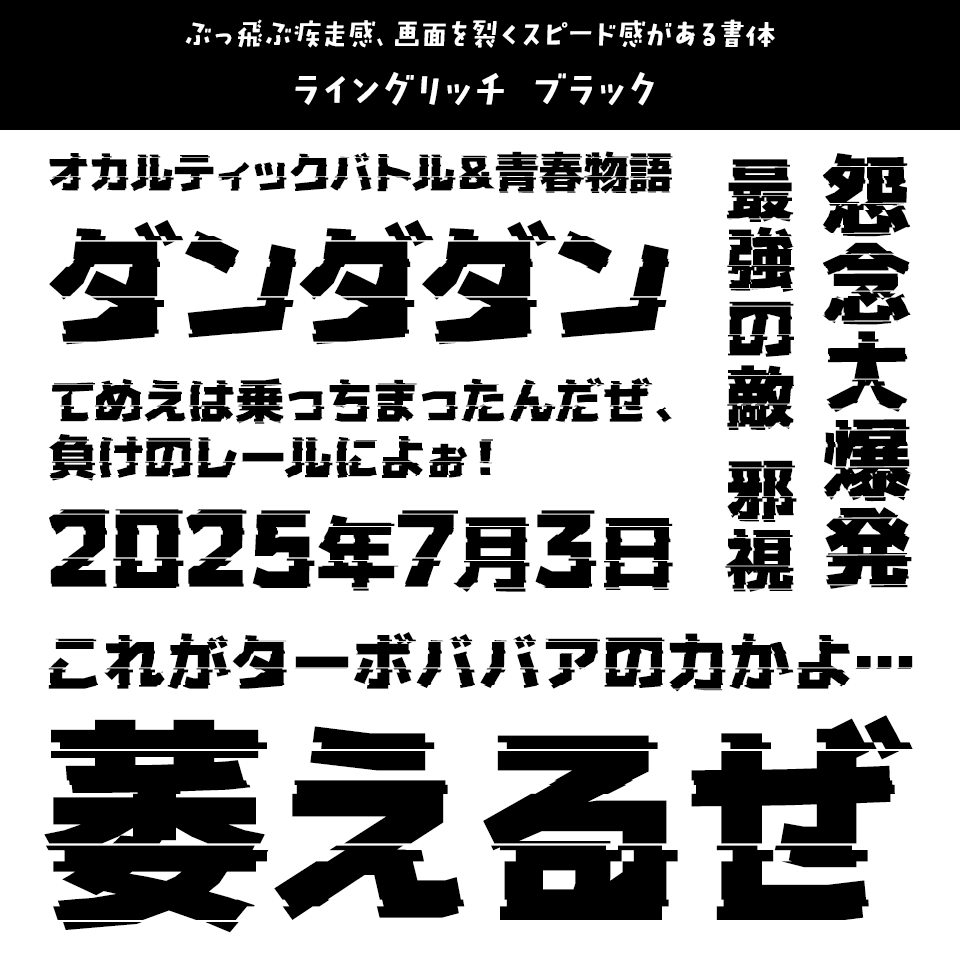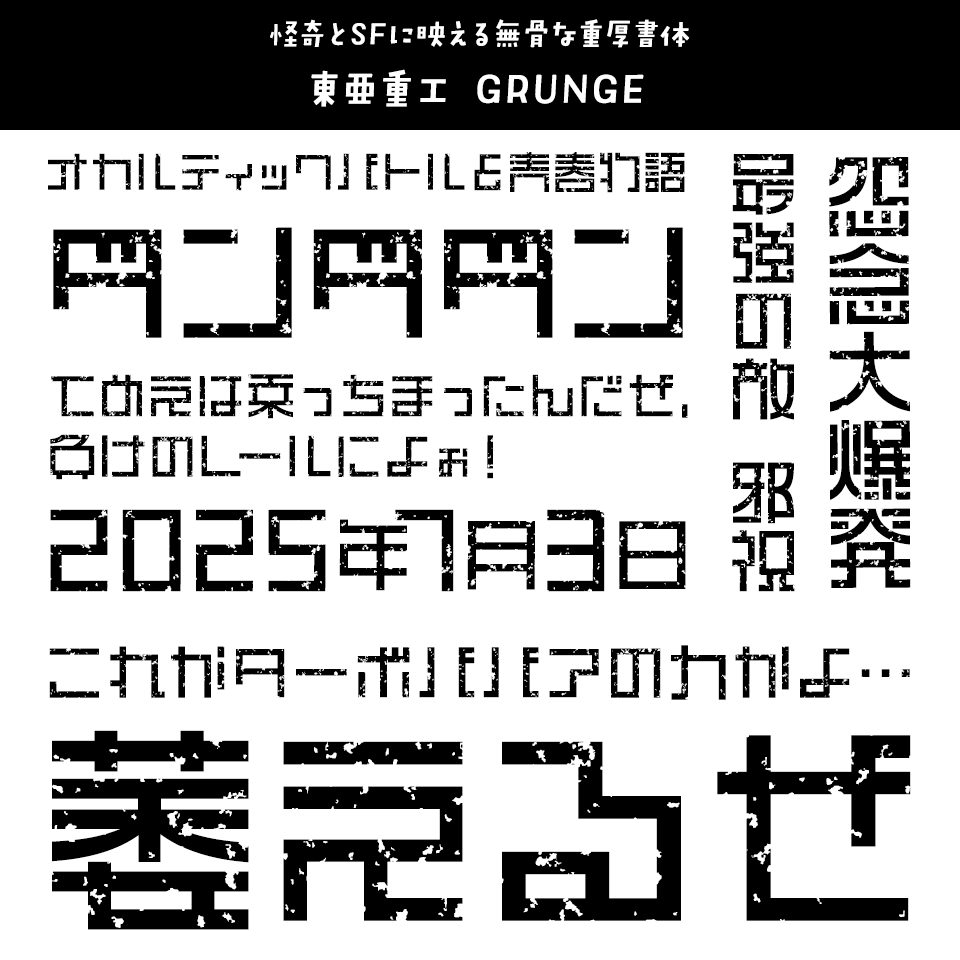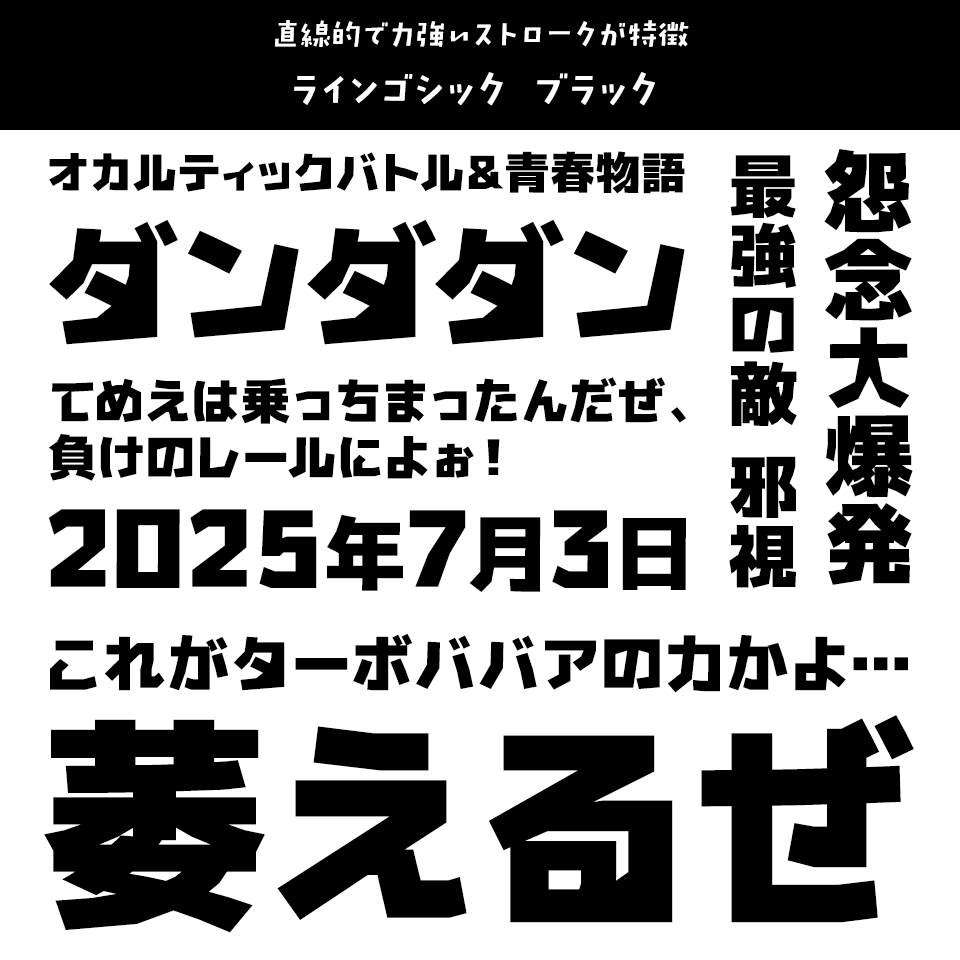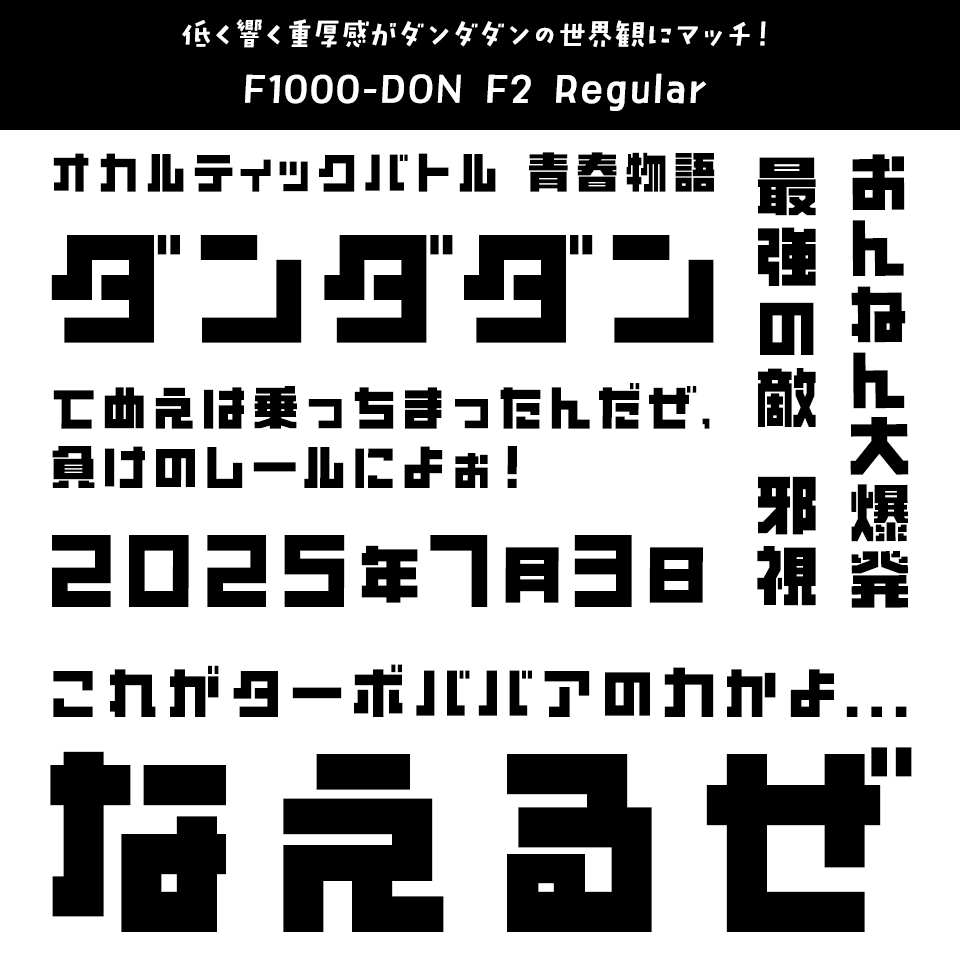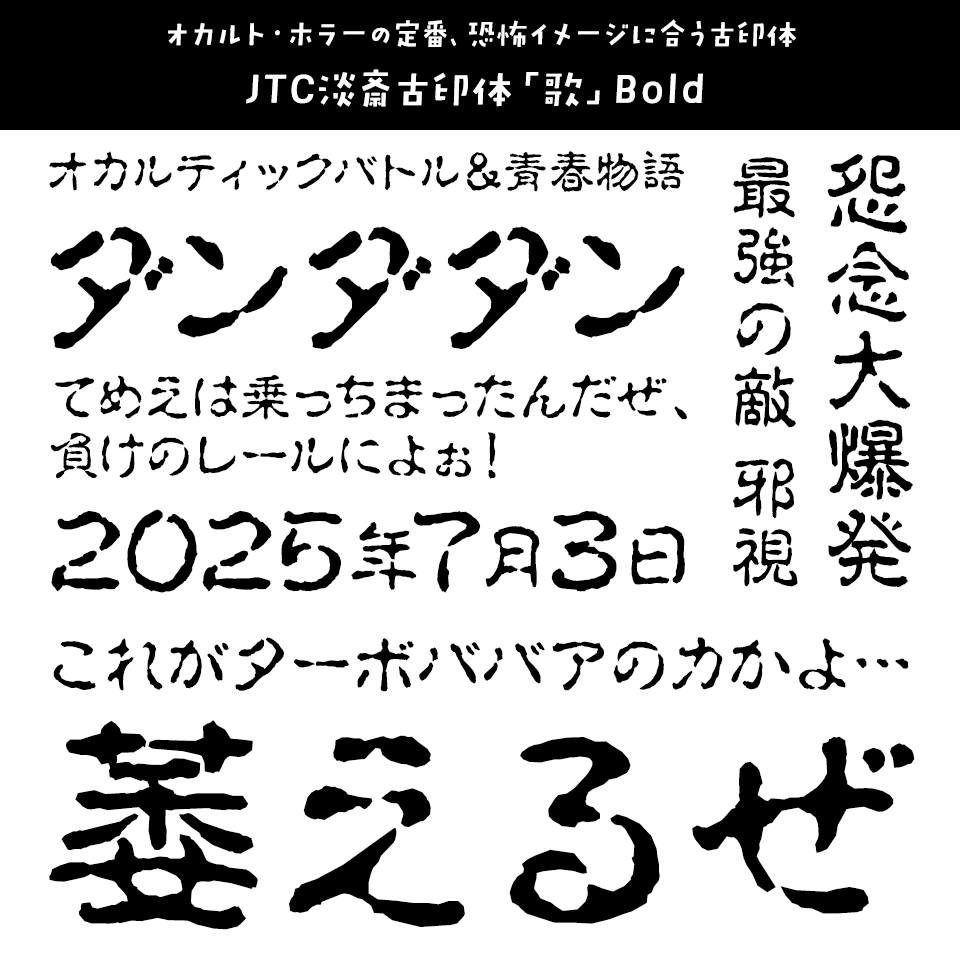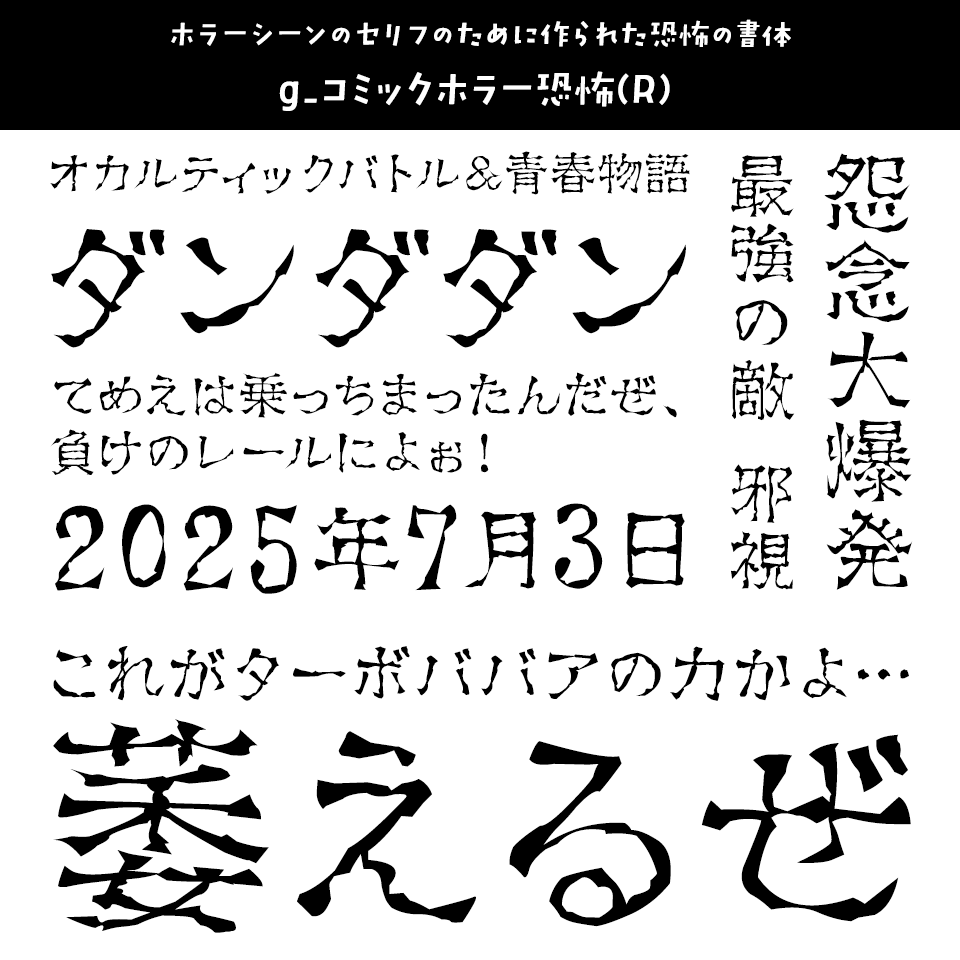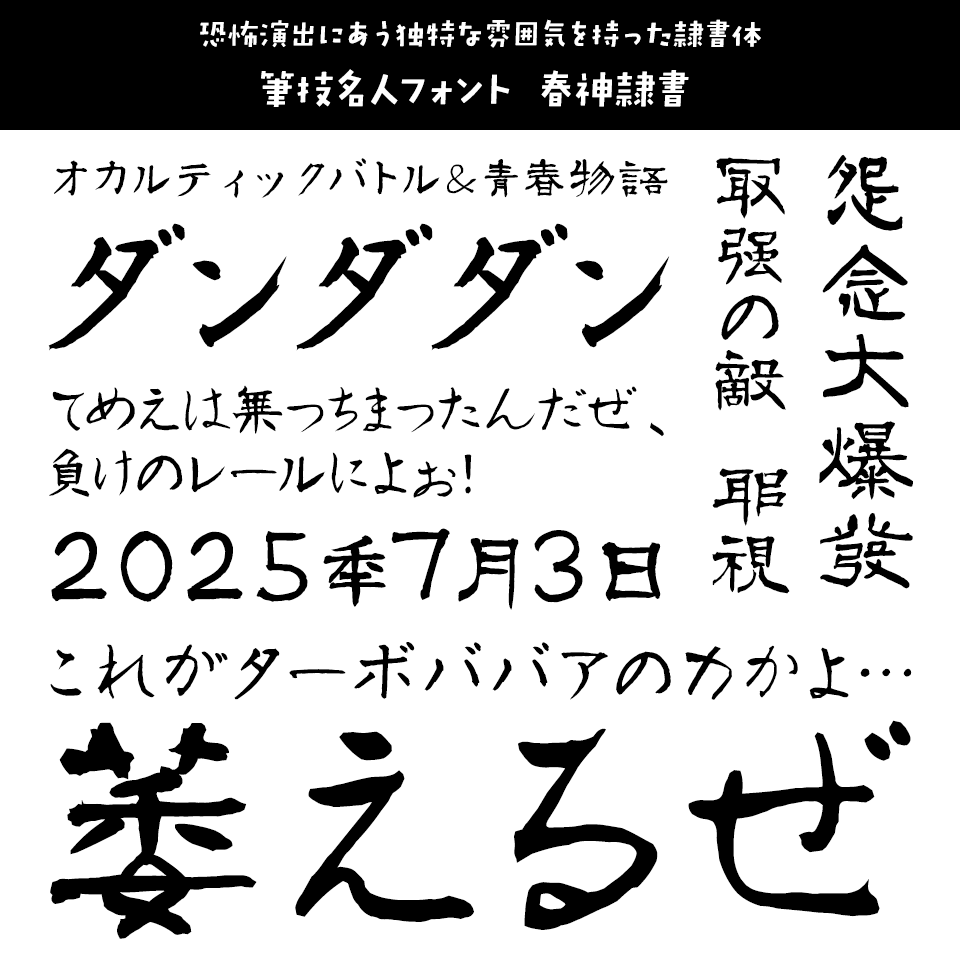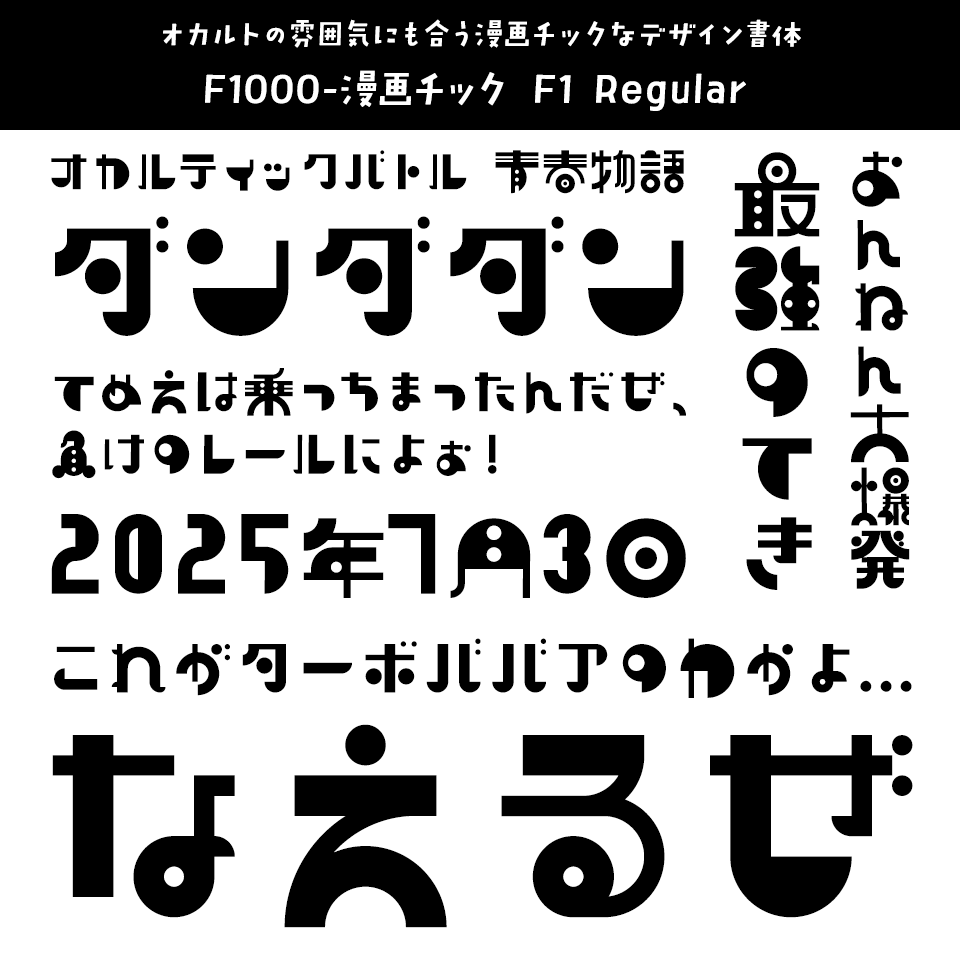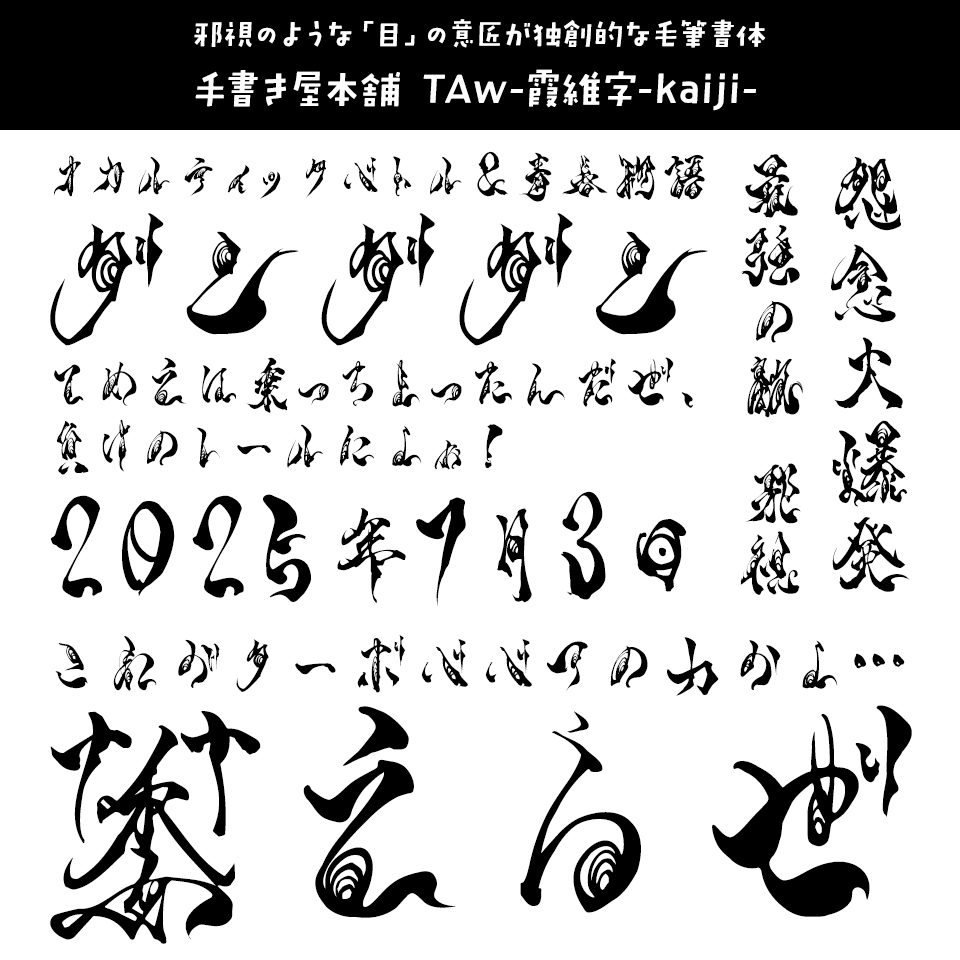
「ダンダダン」に合うフォント 特化型 目的別フォントガイド,オカルト,オカルティック,ターボババア,萎えるぜ,夏,肝試し,アクション
「ダンダダン」に合うフォント:特化型 目的別フォントガイド #178
今回は「ダンダダン」に合うフォント。日々フォントのことばかり考えている当店スタッフが直感的に選んだフォントをご紹介します。
「ダンダダン」に合うフォントをスタッフが選びました
「ダンダダン」に合うフォント ライングリッチ ブラック
ぶっ飛ぶ疾走感、画面を裂くスピード感がある書体
ライングリッチ ブラック【にっぽり】
「ダンダダン」に合うフォント ライングリッチ ブラック
異次元バトルや超常現象のスピード感をそのまま文字に。ライン状のブレと重厚な黒が、「ダンダダン」の激しいアクションや緊張感を完璧に演出します。
「ダンダダン」に合うフォント 東亜重工 GRUNGE
怪奇とSFに映える無骨な重厚書体
東亜重工 GRUNGE【イワタ書体ライブラリー】
「ダンダダン」に合うフォント 東亜重工 GRUNGE
重厚感と汚れ加工が魅力の「東亜重工GRUNGE」。無骨なデザインは「ダンダダン」の持つ怪奇とSFの混在する世界観にマッチします。
「ダンダダン」に合うフォント ラインゴシック ブラック
直線的で力強いストロークが特徴
ラインゴシック ブラック【にっぽり】
「ダンダダン」に合うフォント ラインゴシック ブラック
力強く、かつ現代的な印象を与える「ラインゴシック ブラック」は、「ダンダダン」のダイナミックな展開と相性抜群。重厚なウェイトが怪異の不穏さとキャラクターのエネルギーを視覚的に強調します。
「ダンダダン」に合うフォント F1000-DON F2 Regular
低く響く重厚感がダンダダンの世界観にマッチ!
F1000-DON F2 Regular【FONT1000】
「ダンダダン」に合うフォント F1000-DON F2 Regular
「F1000-DON」は縦横の太いストロークが生む安定感と重厚さが魅力。低く響く「ドン」という擬音のように、ダンダダンの怪奇と勢いある世界観を力強く表現します。
「ダンダダン」に合うフォント JTC淡斎古印体「歌」Bold
オカルト・ホラーの定番、恐怖イメージに合う古印体
JTC淡斎古印体「歌」Bold【ニィスフォント】
「ダンダダン」に合うフォント JTC淡斎古印体「歌」Bold
井上淡斎作の古印体です。独特の筆使いと品のある質感は本来の印鑑から漫画、テレビの「ホラー文字」まで多くのシーンで使用されています。
「ダンダダン」に合うフォント g_コミックホラー恐怖(R)
ホラーシーンのセリフのために作られた恐怖の書体
g_コミックホラー恐怖(R)【よく訓練されたフォント屋】
「ダンダダン」に合うフォント g_コミックホラー恐怖(R)
同作者の「g_コミック古印体」をベースに、コミックのホラーシーンのセリフに使用する事を想定して作成したホラーフォントです。碑文っぽさもあるので歴史モノ等にも。
「ダンダダン」に合うフォント 筆技名人フォント 春神隷書
恐怖演出にあう独特な雰囲気を持った隷書体
筆技名人フォント 春神隷書【ミーネット】
「ダンダダン」に合うフォント 筆技名人フォント 春神隷書
「春神隷書」は、隷書体の中でもより篆書に近く、特徴的な「古隷」を選んで作りました。隷書体、とりわけ古隷を得意とする書家が一文字ずつ書いた、素朴で歴史を感じる隷書体フォントです。
「ダンダダン」に合うフォント イワタアンチック体E ProN
セリフにも見出しにも、太めのアンチック体
イワタアンチック体E ProN【イワタ書体ライブラリー】
「ダンダダン」に合うフォント イワタアンチック体E ProN
イワタアンチック体は、力強いゴシック漢字に筆書き風の柔らかいアンチック仮名を組み合わせたのが特徴で、その表情豊かな書風から漫画の吹き出しなどに多く使われてきました文字種を大幅に拡張したほか、特殊な仮名や絵文字・記号類など遊び心に満ちた文字をアンチック外字として新規追加しています。
「ダンダダン」に合うフォント F1000-漫画チック F1 Regular
オカルトの雰囲気にも合う漫画チックなデザイン書体
F1000-漫画チック F1 Regular【FONT1000】
「ダンダダン」に合うフォント F1000-漫画チック F1 Regular
ゴシックのことをゴチックとも言います。メルヘンぽいことをメルヘンチック、乙女心を乙女チックなどと言います。漫画っぽいゴシック、漫画のタイトル風、みたいな書体を考えてみました。
「ダンダダン」に合うフォント 手書き屋本舗 TAw-霞維字-kaiji-
邪視のような「目」の意匠が独創的な毛筆書体
手書き屋本舗 TAw-霞維字-kaiji-【ウェブフォントジャパン】
「ダンダダン」に合うフォント 手書き屋本舗 TAw-霞維字-kaiji-
霞維字は「文字」がある認識は一瞬であるが、読む行為は時間を費やすデザインになっております。又、目を模した文字であり、見られている感覚を意識して相手に文字以上の情報を提供しております。ですので、絵や背景に溶け込ませたり、文字反転との組み合わせ等、文字以外の使い方も可能です。